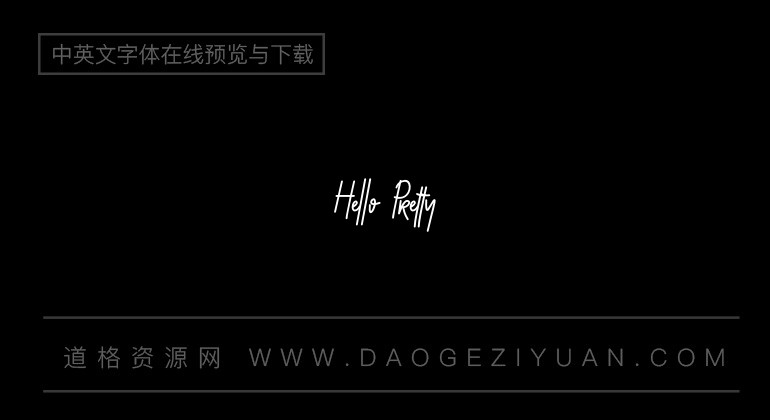
Hello Pretty
Hello Pretty 是一种优雅的手写字体,具有流畅的笔画和漂亮的外观。它是由美国字体设计师 Nicky Laatz 设计的,可在许多不同的项目中使用,如印刷品、贺卡、海报、包装和网站设计等。这种字体有很多不同的样式和大小,因此可以根据需要进行定制。Hello Pretty 字体非常适合需要传达一种柔和、亲切、温馨感觉的设计项目。
Hello Pretty是一款非常不错的手写艺术字体,具有很好的视觉感,适合于文化类的宣传设计、商业类品牌的广告和产品包装设计以及个性化文字排版等较多场景。